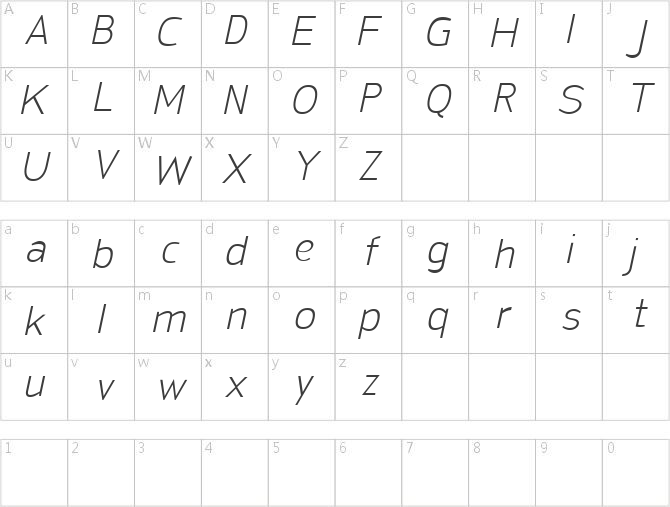
san_frediano_light_italic
san_frediano_light_italic介绍
san_frediano_light_italic字体字库是一款让人赏心悦目、百看不厌的英文字体,适合各类广告和产品包装设计应用,字体大小0.12MB,格式为ttf字体,上传用户是ㄚòひ慬偶鰢,作者/版权方为未知